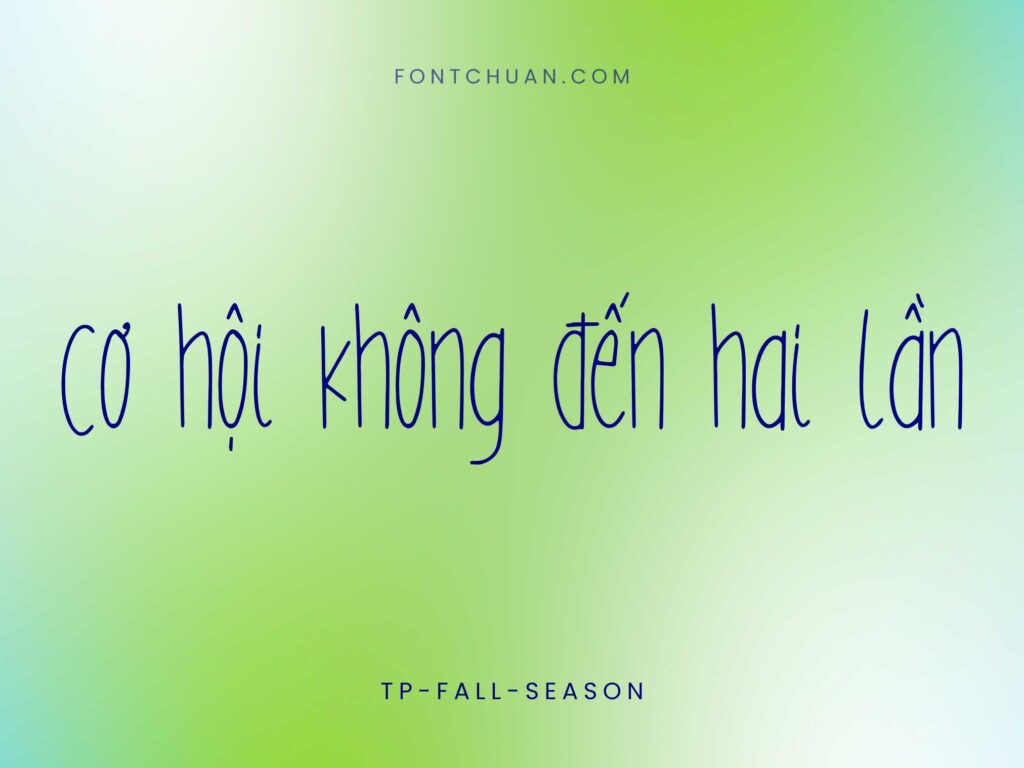
Font TP Fall Season Việt Hóa
Fall Season là một font chữ viết tay mang lại cảm giác thư thái và một chút hoài niệm, được thiết kế bởi Jen Wagner. Font này là lựa chọn tuyệt vời để tạo ra các logo bắt mắt, thương hiệu và trích dẫn. Font đã được Việt hóa để hỗ trợ tiếng Việt bởi Tuỳn Pucca, đồng thời hỗ trợ nhiều ngôn ngữ khác, giúp mở rộng phạm vi sử dụng trên toàn cầu. Font này được sưu tầm và chia sẻ bởi thành viên của Font Chuẩn, đáp ứng nhu cầu của người dùng và ứng dụng thực tế vào các dự án thiết kế.
Đặc điểm thiết kế của Fall Season bao gồm các nét chữ mềm mại và tự nhiên, tạo cảm giác ấm áp và thân thiện. Font này phù hợp cho các ứng dụng như tiêu đề, logo, thiệp mời và các dự án sáng tạo khác. Các ngành nghề phù hợp bao gồm quảng cáo, giáo dục và thiết kế đồ họa.